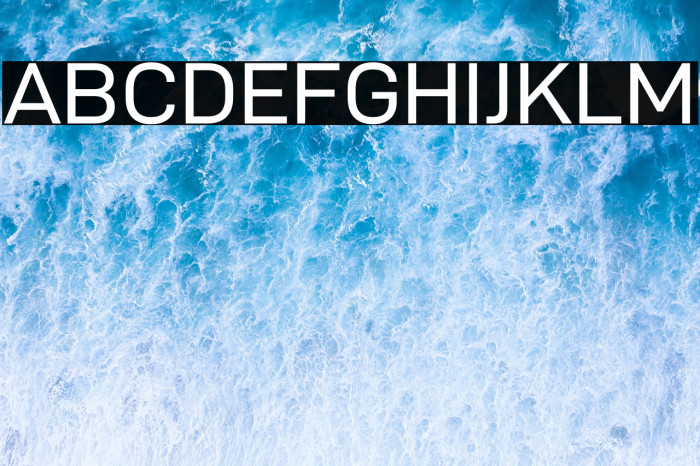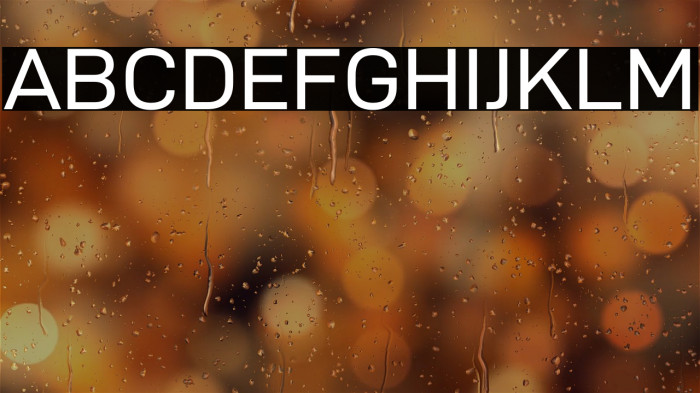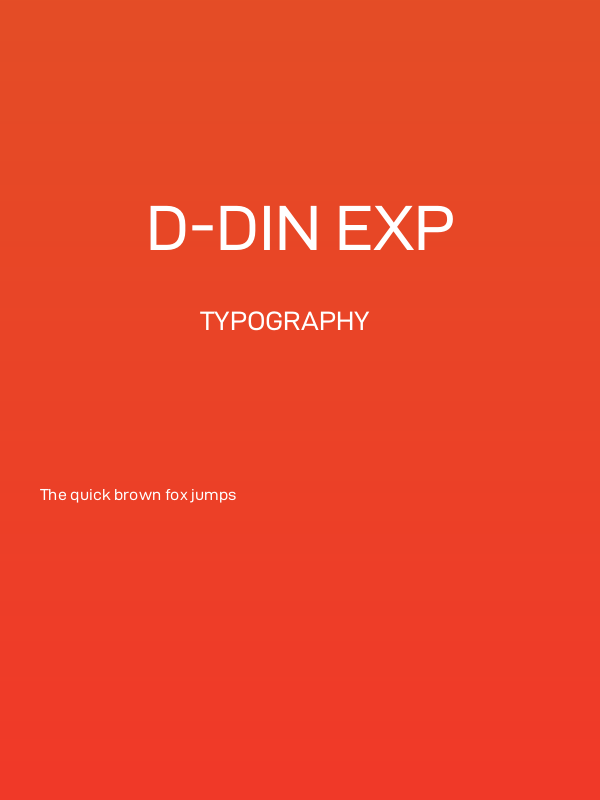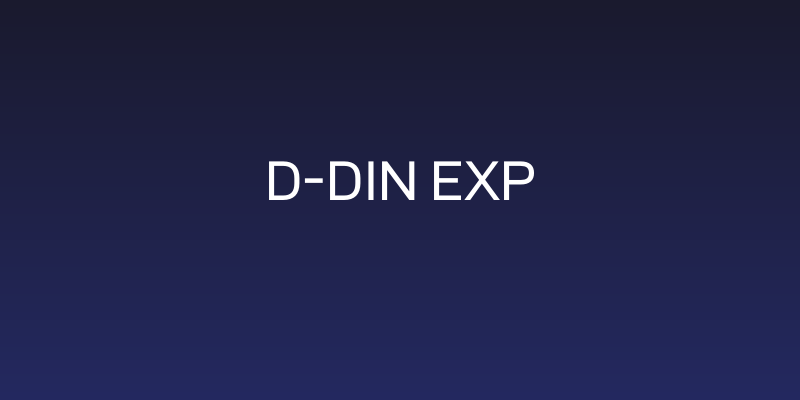
D-DIN Exp Font
| Anwendungsfall | Headlines, Body text, Logos |
| Vorgeschlagene Projekte | Ideal for corporate branding, user interfaces, signage, and editorial design. |